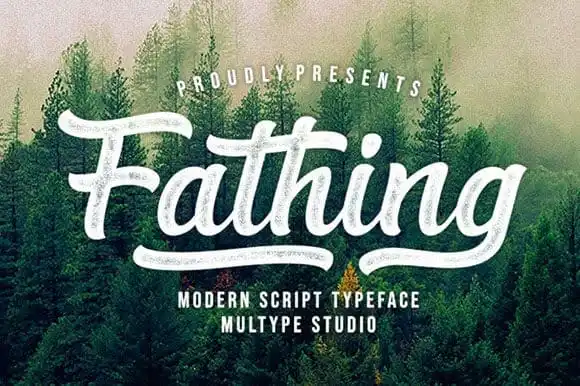
A Fathing Calligraphy Font é inspirada nas obras urbanas ou freestyle. Seu estilo casual e sua gama significativa de alternativas estilísticas permitem criar cabeçalhos realistas. Este design foi criado pelo designer MultypeStudio, que mantém seu clássico influente da escrita e a sensação contemporânea e fresca ao mesmo tempo. Com sua versatilidade extrema, ela se alinha perfeitamente com uma variedade de ideias artísticas, incluindo cartões de boas-vindas, títulos, e material de estação. Esta font é ideal para designers em busca de algo diferente que possa dar um toque único a seus projetos gráficos.